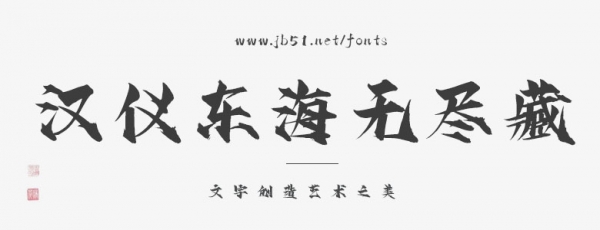
漢儀東海無盡藏是一款由漢儀簽約作者李東海創(chuàng)作的手書字體,給出了極富生命力的答案:豪放遒勁之中又流淌著青澀。這款字體獨特的書寫形式結合了中國傳統(tǒng)書法與西方街頭涂鴉,東方與西方、傳統(tǒng)與現(xiàn)代、經(jīng)典與叛逆,多重審美碰撞之下誕生的這款字體有著強烈的風格特征,結字富于節(jié)奏,筆畫渲染不羈。這款字體適用于潮流品牌、書刊雜志、影視廣告等各種場景。